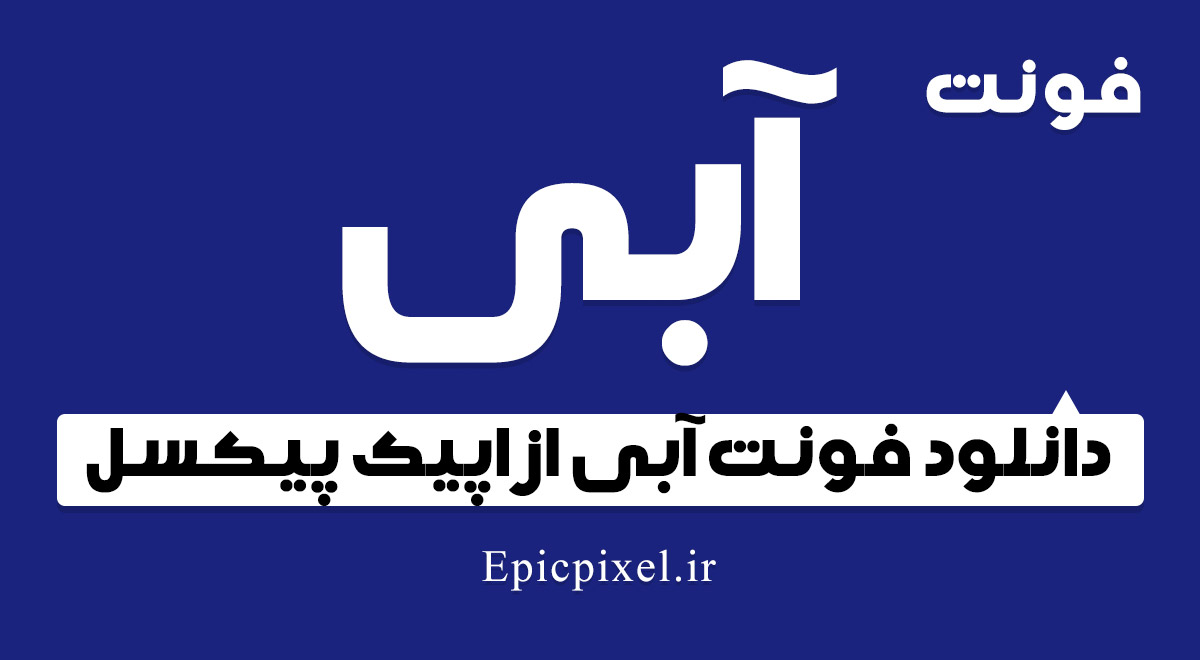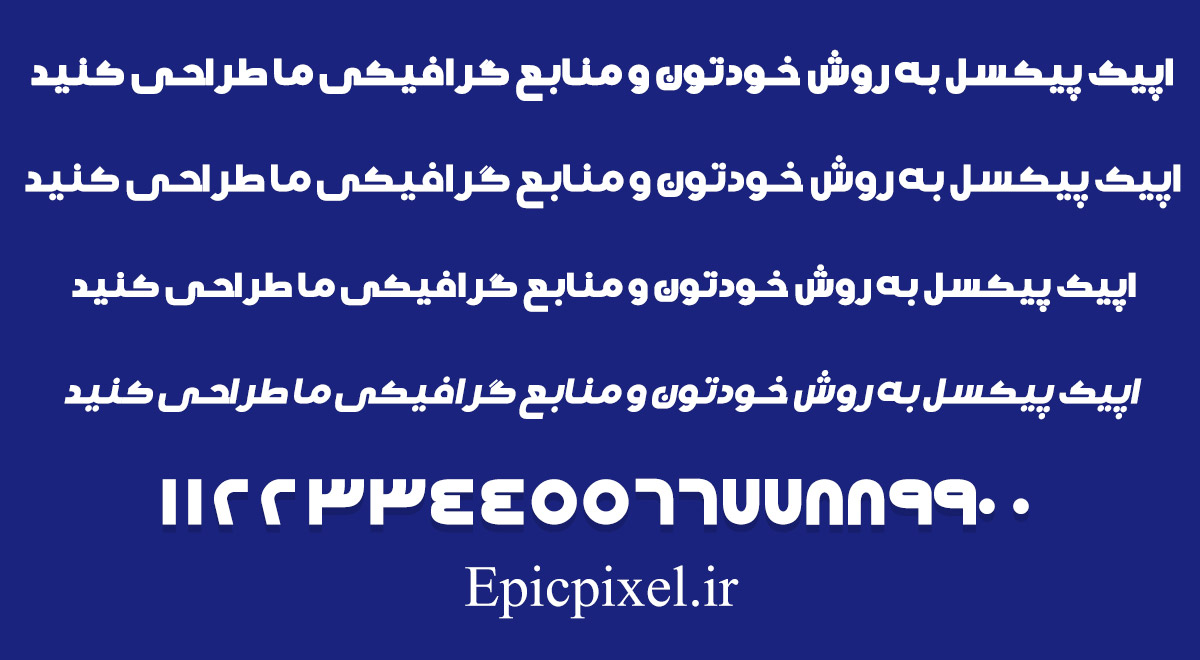
11 فونت آبی فارسی
دانلود فونت Blue فارسی Font آبی |
| ⭐ توضیحات | مجموعه ای کامل از فونت های آبی و نسخه شبیه سازی شده بنام اپیک ابی فونت اپیک ابی با پشتیبانی از حروف فارسی، اعداد فارسی Fu Num بهمراه نسخه وب و نسخه وریبل متغییر ( عدم پشتیبانی از انگلیسی ) بهمراه یک فونت مشابه آبی |
فونت آبی یک فونت هندسی مدرن و خلاقانه
فونت آبی یک فونت هندسی است که با هدف طراحی وبسایتها، تبلیغات و نشریات مدرن طراحی شده است. این فونت با ضخامت یکسان، زاویههای مسطح، حروف جایگزین و قابلیت ترکیب با فونتهای لاتین، میتواند جذابیت، خلاقانهگی و مدرن بودن نوشتار را افزایش دهد. در این مقاله، به معرفی، کاربردها و نکاتی برای استفاده بهینه از این فونت پرداختهایم.
معرفی فونت آبی
هدف از طراحی فونت آبی
هدف اصلی از طراحی فونت آبی، طراحان رابط کاربر را قادر ساختن به استفاده از چیدمان حروف منظم در صفحات نمایش رایانه و تلفن همراه با حجم کم در حال حاضر و در آینده است.
ویژگیها و مزایای فونت آبی
فونت آبی دارای ویژگیها و مزایای زیر است:
– ضخامت یکسان و زاویههای مسطح که باعث مدرن بودن و جذابیت فونت میشود.
– حروف جایگزین برای برخی از حروف که باعث افزایش تنوع و کاهش تکرار در نوشتار میشود.
– قابلیت ترکیب با فونتهای لاتین، که باعث سازگاری با زبانهای مختلف و افزایش امکانات طراحی میشود.
– پشتیبانی از حروف عربی، که باعث مناسب بودن برای نوشتار دینی و فرهنگی میشود.
– فونت متغیر (وریبل فونت)، که باعث کاهش حجم فایلها و افزایش سرعت لود صفحات وب میشود.
نسخهها و وزنهای مختلف فونت آبی
برخی از این تغییرات در نسخه های مختلف عبارتند از:
– اضافه شدن چیدمان جدید برای حروف «آ»، «ئ»، «پ»، «چ»، «ژ»، «ک»، «گ»، «م»، «ھ»، «ۀ»
– اضافه شدن حالت جدید برای نقطه حروف
– اضافه شدن حالت جدید برای اعداد
– اضافه شدن حالت جدید برای علامات نقطهگذاری [^1^][1]
فونت آبی در چند وزن در دسترس است. همچنین دارای دو محور، تغییر وزن (weight) و تغییر نقطه (dots) است که باعث افزایش قابل خواندن بودن فونت در سایزهای مختلف میشود.
کاربردهای فونت آبی
وبسایتها و نرمافزارها
فونت آبی یک فونت مناسب برای طراحی وبسایتها و نرمافزارها است که نیاز به جلب توجه و انتقال پیام به صورت بصری دارند. این فونت با ساختار هندسی و قابلیت ترکیب با فونتهای لاتین خود، میتواند طرح را زیباتر و مدرنتر کند و پیام را به زبانهای مختلف منتقل کند. برای مثال، میتوان از این فونت برای طراحی منوها، عناوین، دکمهها و لیبلها استفاده کرد.
تبلیغات و برندینگ
فونت آبی یک فونت مناسب برای تبلیغات و برندینگ است که نیاز به جلب توجه و انتقال پیام به صورت صریح دارند. این فونت با ضخامت یکسان و شخصیت متفاوت خود، میتواند هویت برند را تقویت کند و مخاطب را به خود جذب کند. برای مثال، میتوان از این فونت برای طراحی لوگو، اسلوگان، بنر، کاتالوگ و بستهبندی استفاده کرد.
نشریات و کتابهای مدرن
فونت آبی یک فونت مناسب برای نشریات و کتابهای مدرن است که نیاز به ایجاد تازگی و درگیر کردن ذهن خواننده دارند. این فونت با ساختار متفاوت و حروف جایگزین خود، میتواند جذابیت نوشتار را افزایش دهد و محتوای معاصر و آینده گرا را بهتر منعکس کند. برای مثال، میتوان از این فونت برای طراحی جلد کتاب، عناوین فصلها، مقالات علمی و روزنامههای الکترونیکی استفاده کرد.
نکاتی برای استفاده بهینه از فونت آبی
توجه به سازگاری با سبک طراحی
فونت آبی یک فونت با ساختار هندسی است که ممکن است با بعضی از سبکهای طراحی همخوانی نداشته باشد. بنابراین، لازم است در هنگام استفاده از این فونت، به سازگاری با سبک طراحی توجه شود. برخی از راههای دست یابی به این همخوانی عبارتند از:
استفاده از فونت آبی برای سبکهای طراحی مدرن، خلاقانه و هندسی و اجتناب از سبکهای طراحی کلاسیک، سنتی و طبیعی
استفاده از فونت آبی برای موضوعات مرتبط با تکنولوژی، علم، هنر و فلسفه و اجتناب از موضوعات مرتبط با تاریخ، ادبیات، دین و فرهنگ
استفاده از فونت آبی برای مخاطبان جوان، مدرن و خلاق و اجتناب از مخاطبان پیر، سنتی و محافظهکار
توجه به خوانایی در سایزهای مختلف
فونت آبی یک فونت با شخصیت قوی است که ممکن است در بعضی سایزها باعث کاهش خوانایی شود. بنابراین، لازم است در هنگام استفاده از این فونت، به خوانایی در سایزهای مختلف توجه شود. برخی از راههای دست یابی به این خوانایی عبارتند از:
استفاده از فونت آبی برای عناوین و متون کوتاه و استفاده از فونتهای روان برای بدنه متن
استفاده از سایزهای مناسب برای فونت آبی و اجتناب از سایزهای بسیار کوچک یا بسیار بزرگ
استفاده از دو محور تغییر وزن (weight) و تغییر نقطه (dots) برای بهبود خوانایی در سایزهای کوچک
توجه به استفاده از فونت متغیر
فونت آبی یک فونت متغیر (وریبل فونت) است که باعث کاهش حجم فایلها و افزایش سرعت لود صفحات وب میشود. بنابراین، لازم است در هنگام استفاده از این فونت، به استفاده از فونت متغیر توجه شود. برخی از راههای دست یابی به این استفاده عبارتند از:
استفاده از دستورات CSS برای تغییر وزن (font-weight) و نقطه (font-variation-settings) فونت آبی